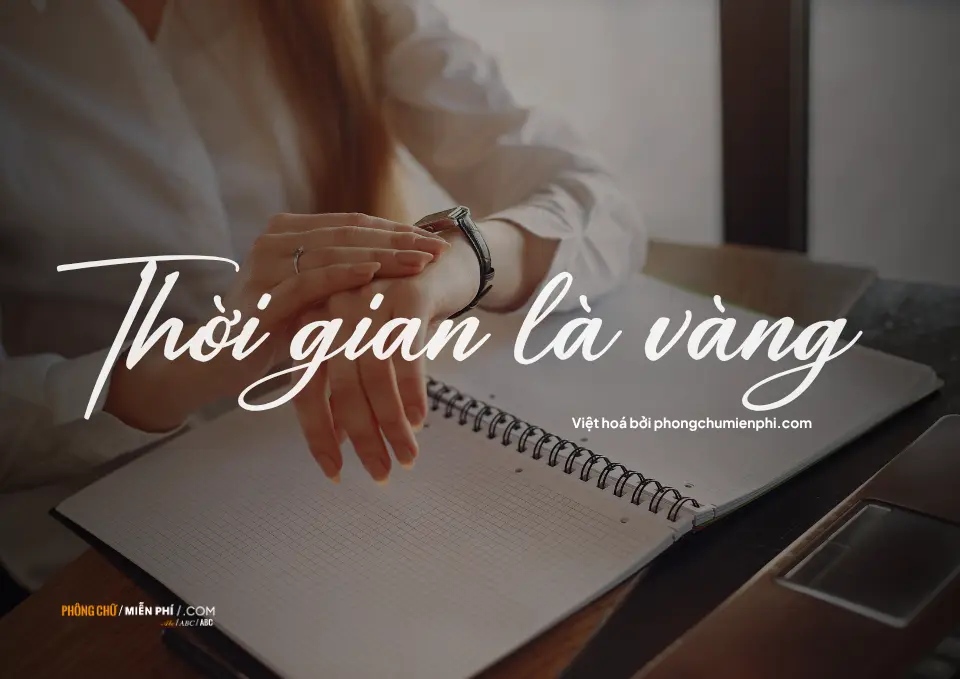
Tên font: Font Việt Hoá Alexandria Signature
Font Việt Hoá PCMP Alexandria Signature
PCMP Alexandria Signature là một phông chữ Signature hiện đại được thiết kế theo phong cách thanh lịch và chuyên nghiệp với các ký tự thay thế. Phông chữ hoàn hảo để tạo logo chữ ký và hình mờ cho các studio nhiếp ảnh hoặc logo nhiếp ảnh cá nhân, lý tưởng cho logo chữ cái đầu hoặc chữ ký thương hiệu.
PCMP Alexandria Signature bao gồm một bộ đầy đủ các chữ cái viết tay đẹp mắt, chữ hoa và chữ thường, số, các dấu câu đa dạng. Tất cả các chữ cái viết thường đều có nét bắt đầu và kết thúc, mang đến phong cách viết tay chân thực.